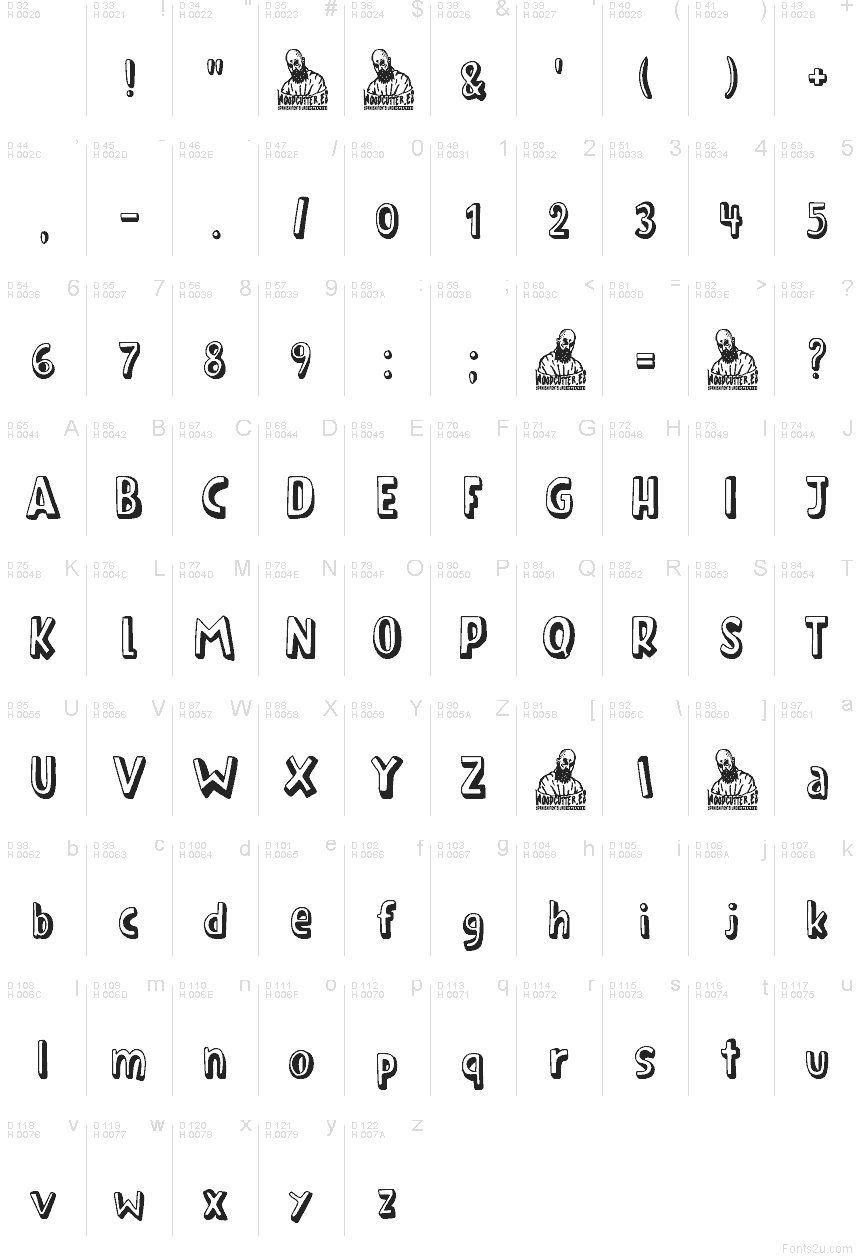
Soprano's Pizza
Soprano's Pizza od Woodcutter Manero je bezplatné komiksové písmo typu display s nádechem starých pizzerií. Písmena působí nadýchaně a ručně kresleně, s oblenými křivkami, kolísavou tloušťkou tahů a výrazným stínováním, které dodává každému nápisu řízný, komiksový vzhled.
Hodí se na jídelní lístky, letáky s jídlem, branding food trucků, retro cedule i hravé obaly – zkrátka všude tam, kde krátký titulek potřebuje ten správný sousedský šmrnc. Jako font zdarma se skvěle hodí i na titulky plakátů, obálky nebo skici log, protože jeho živé kontury dodají i pár slovům pořádnou dávku charakteru a energie.